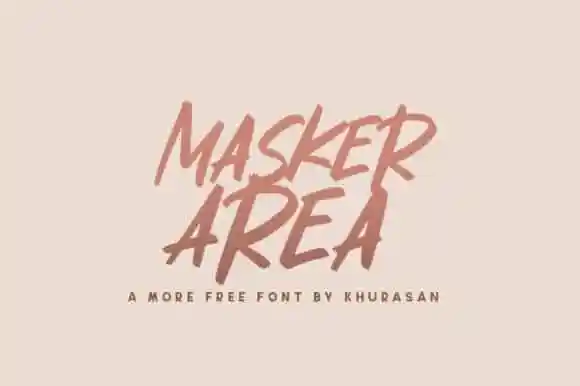
Masker Area Brush Font – Fonte Grátis
Masker Area Brush Font
A Masker Area Brush Font é uma fonte de script marcador gratuita criada por Khurasan com traços arredondados e personagens divertidos. Esta fonte é perfeitamente adaptável para uso nos anúncios, logotipos e em qualquer outra design que exigir um visual atraente e cool! Quer você esteja criando uma marca de sucesso ou apenas quer impressionar os seus clientes com seu trabalho, esta fonte é o ideal. Faça algo realmente impressionante usando a Fonte de Marcador Direto da Khurasan.